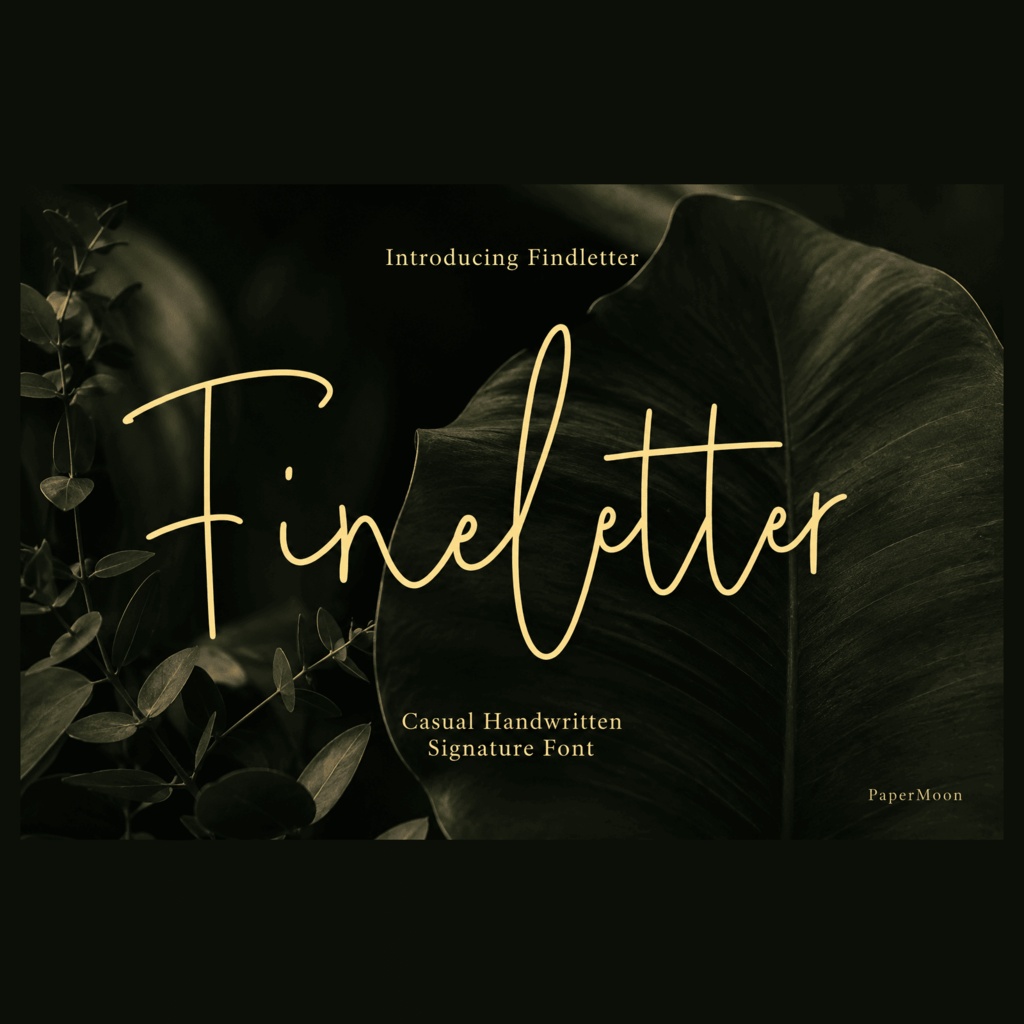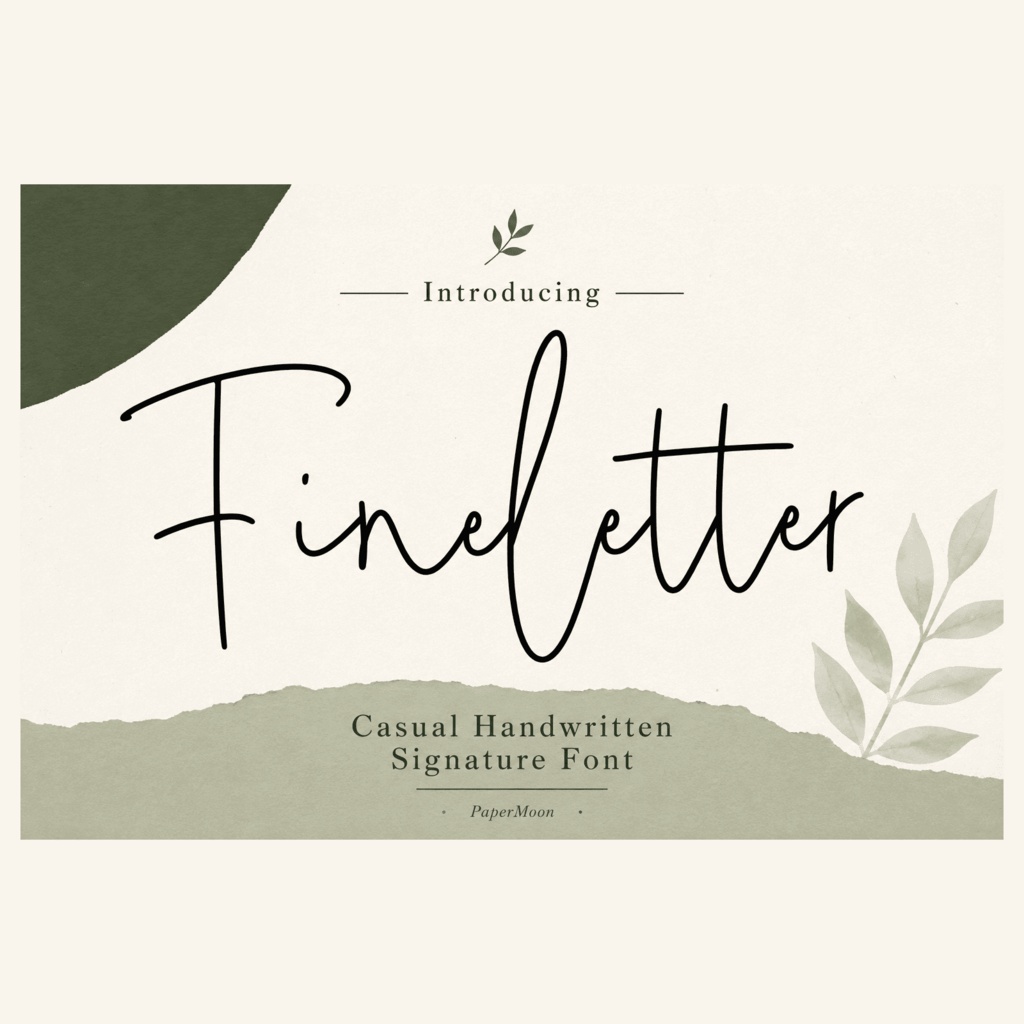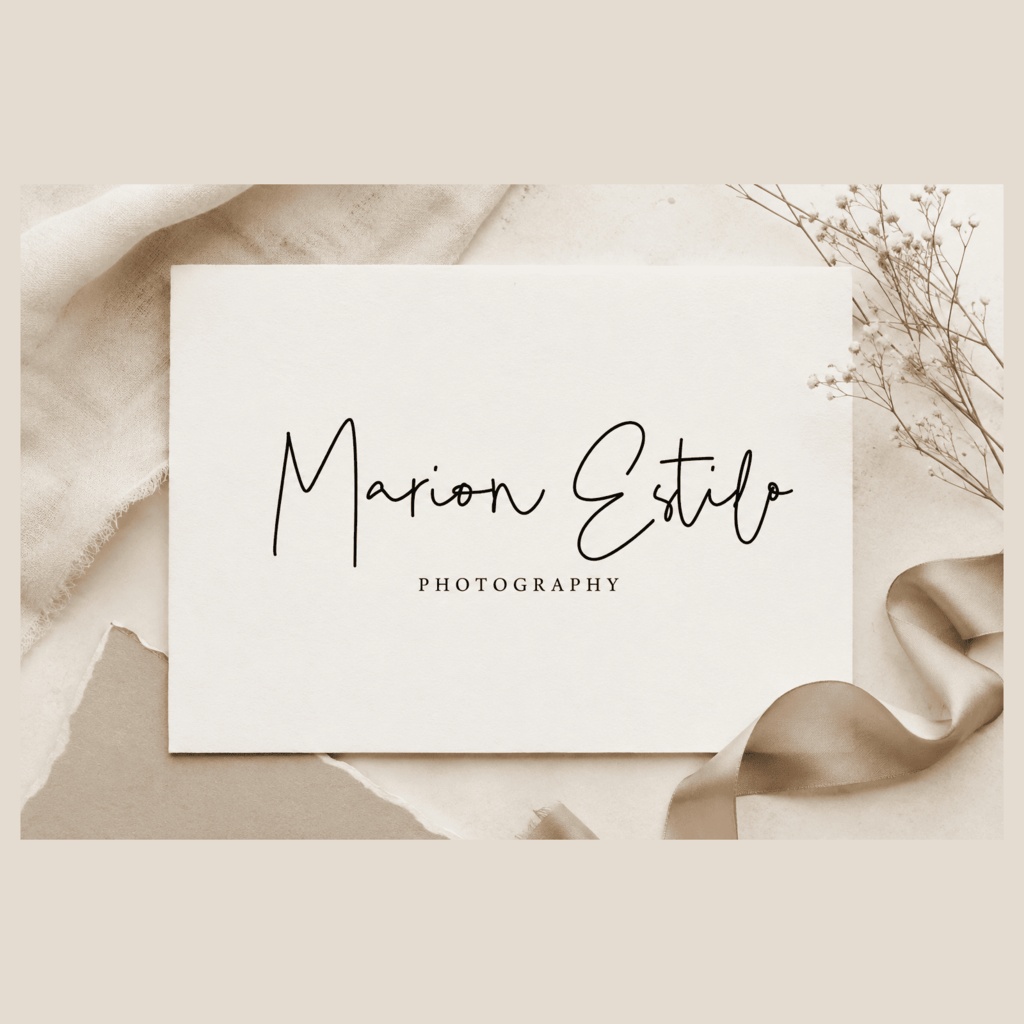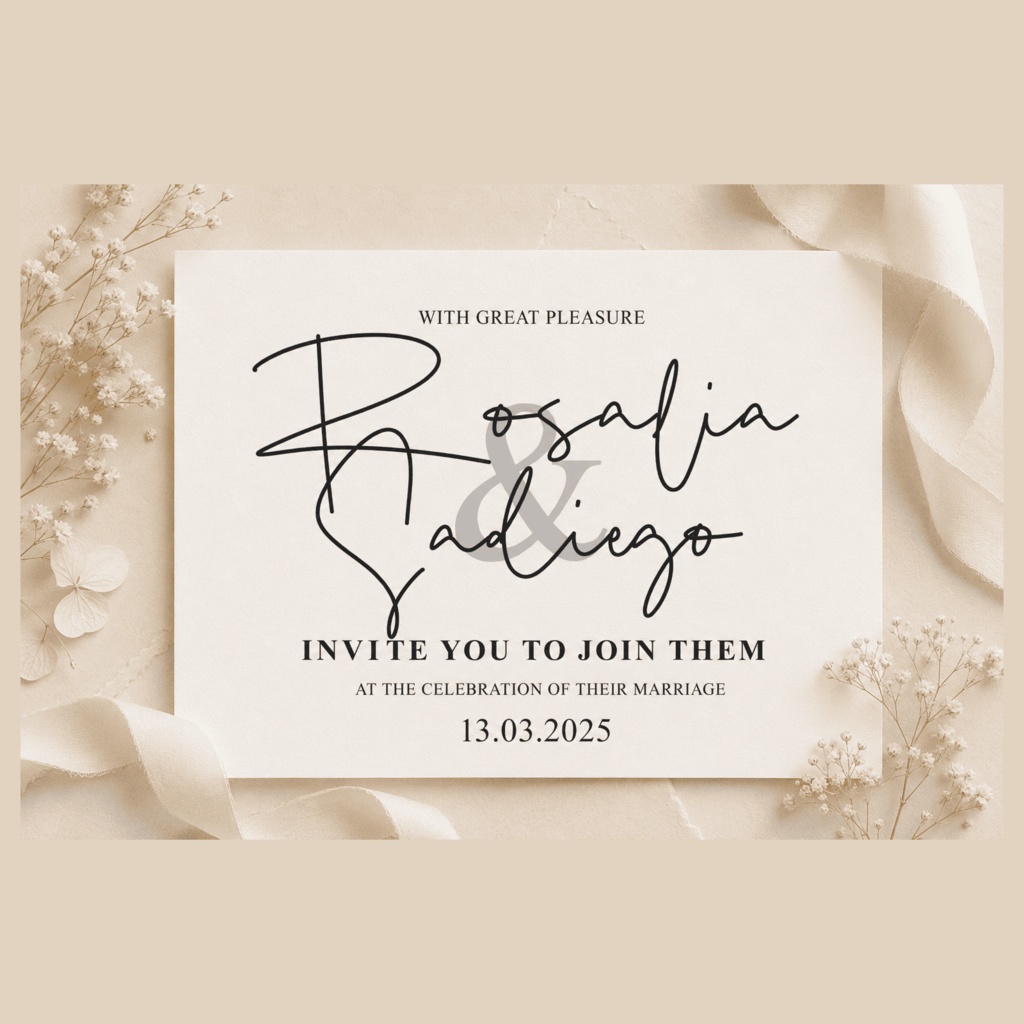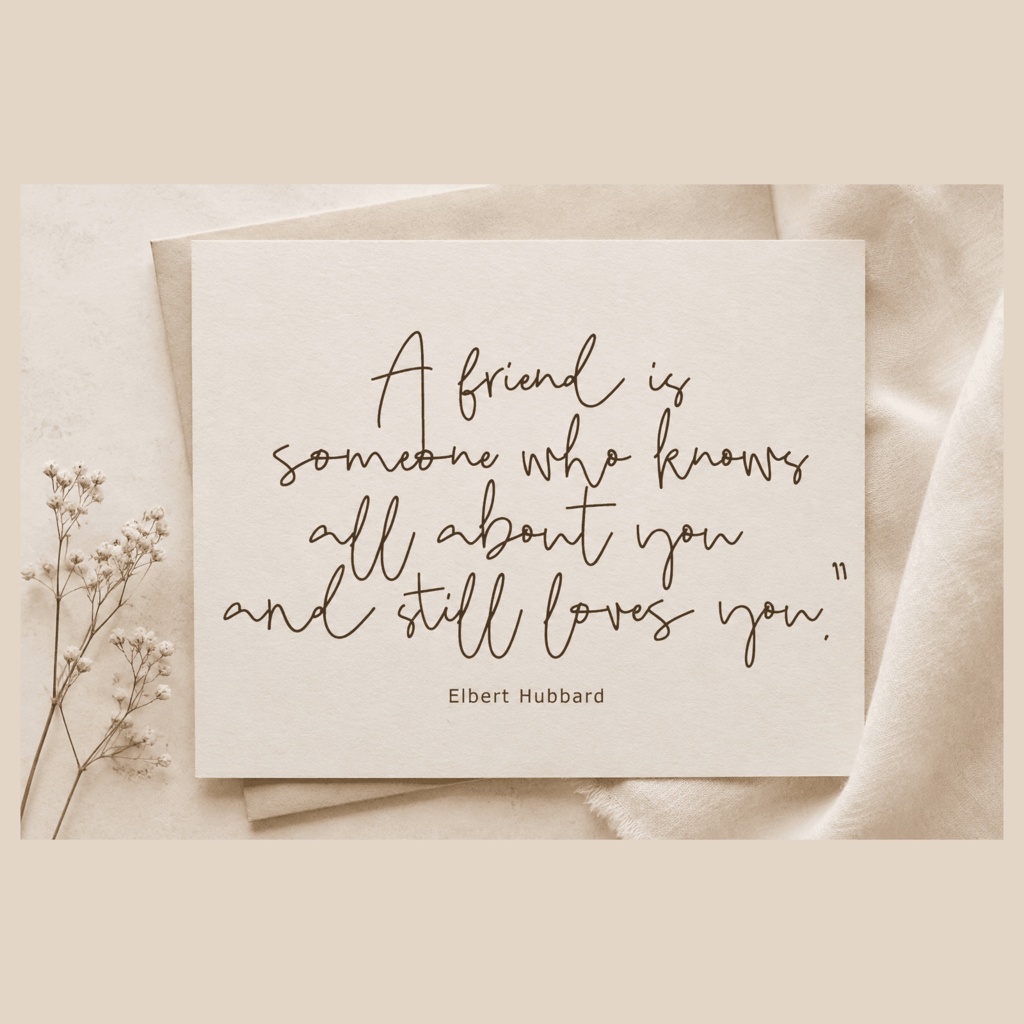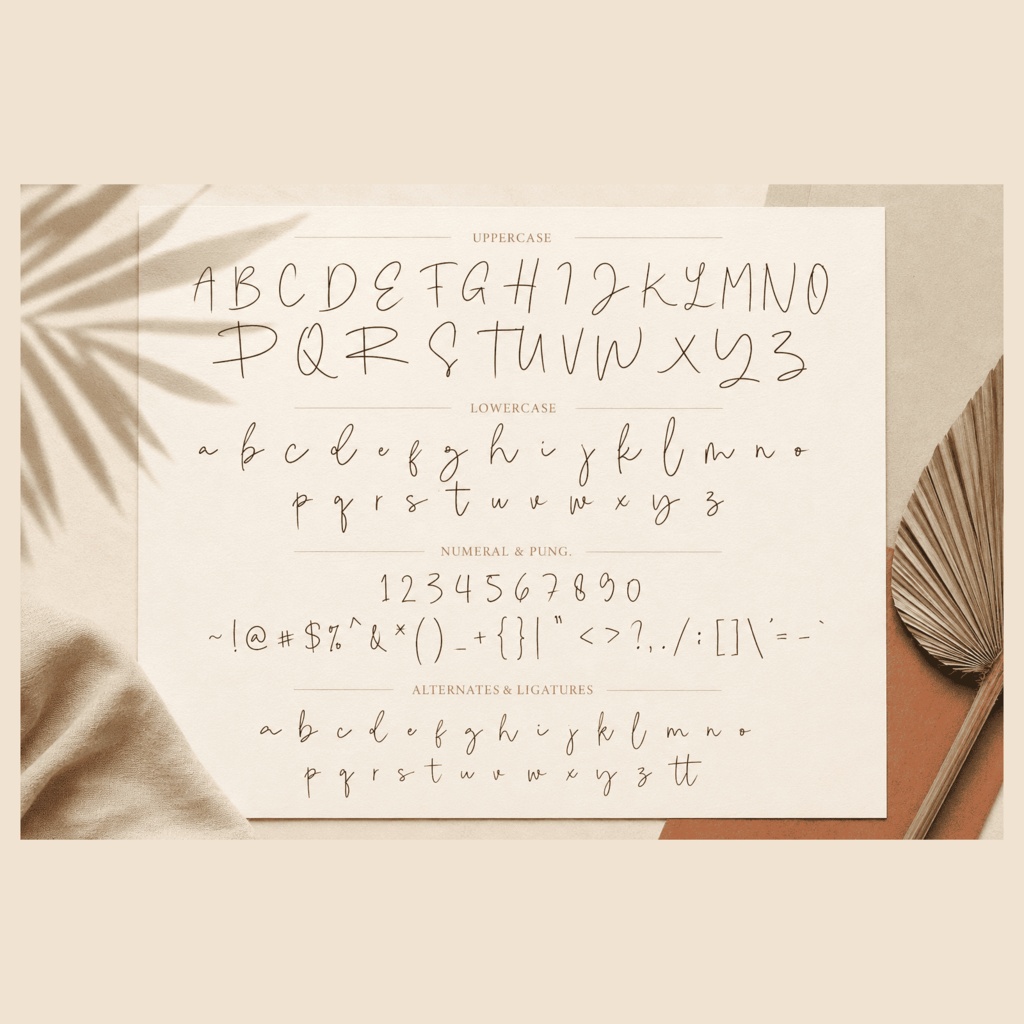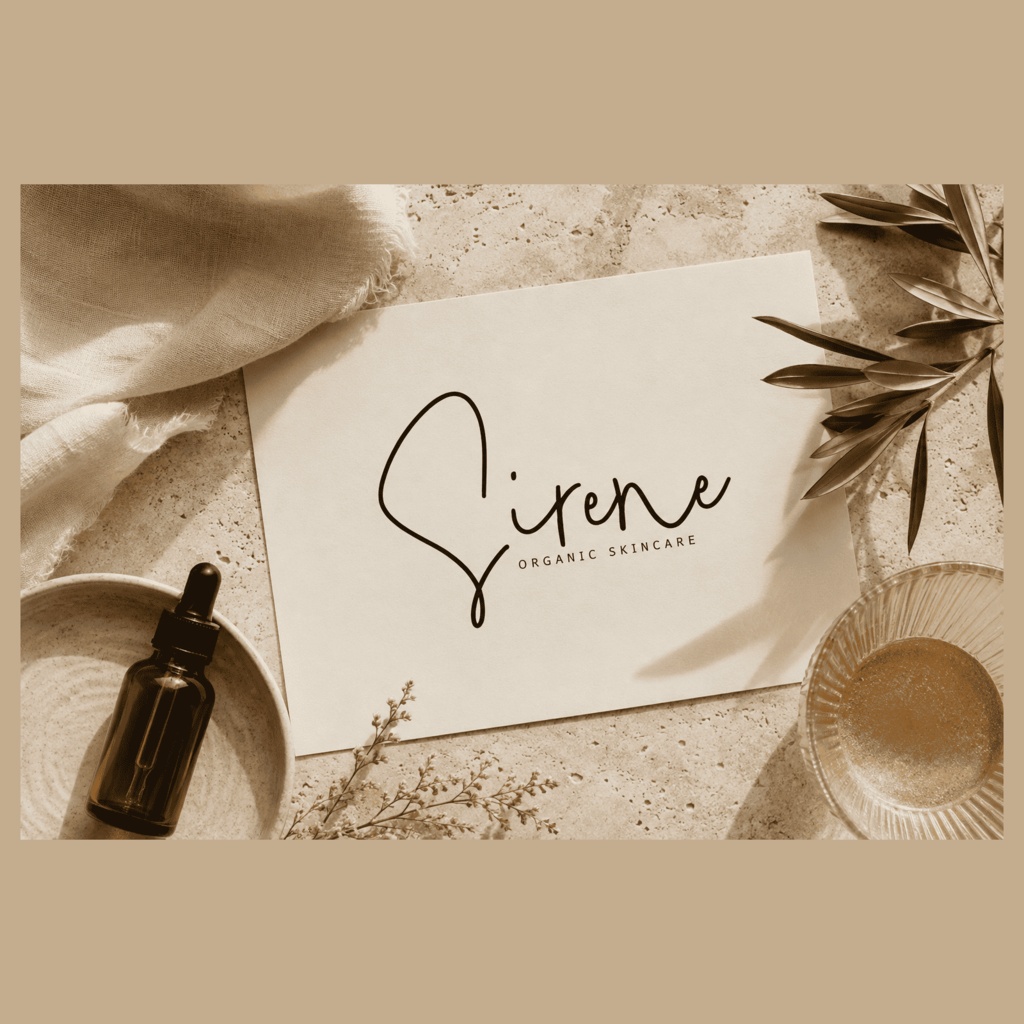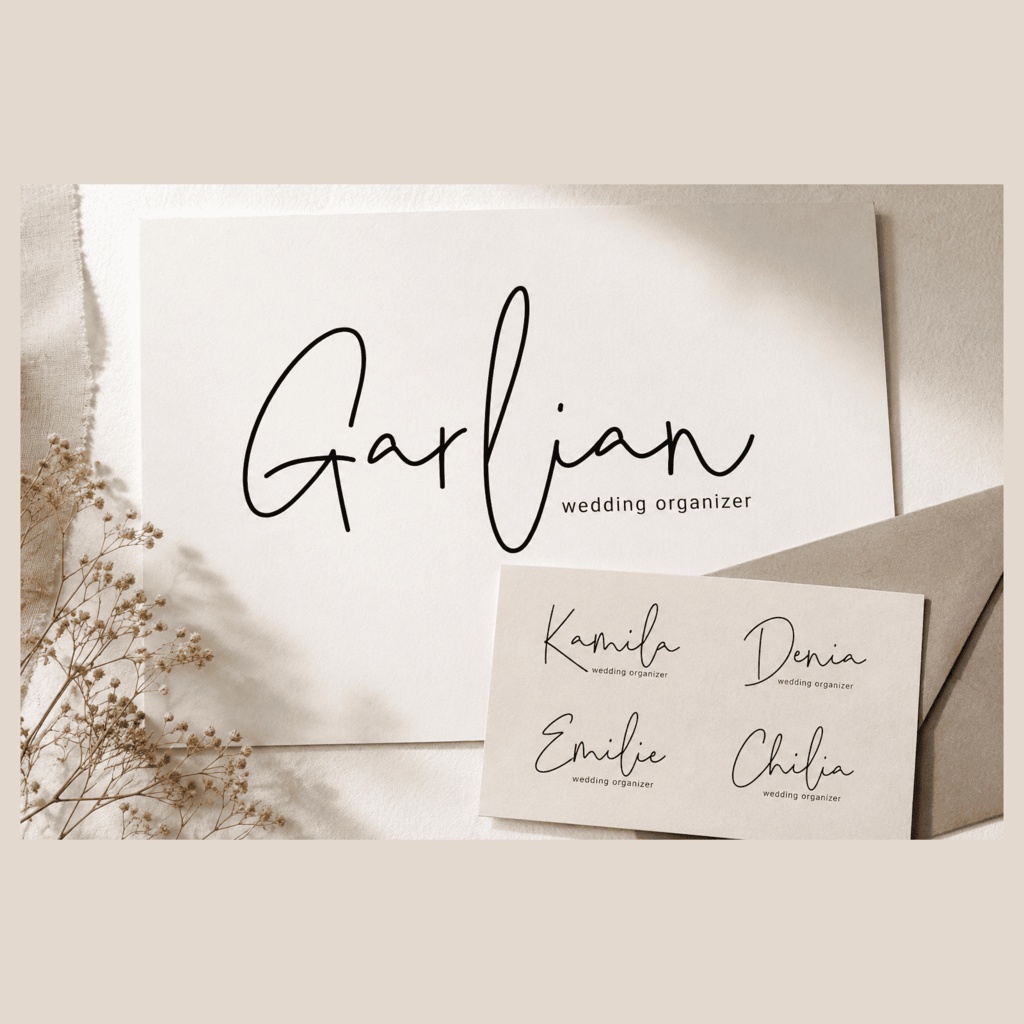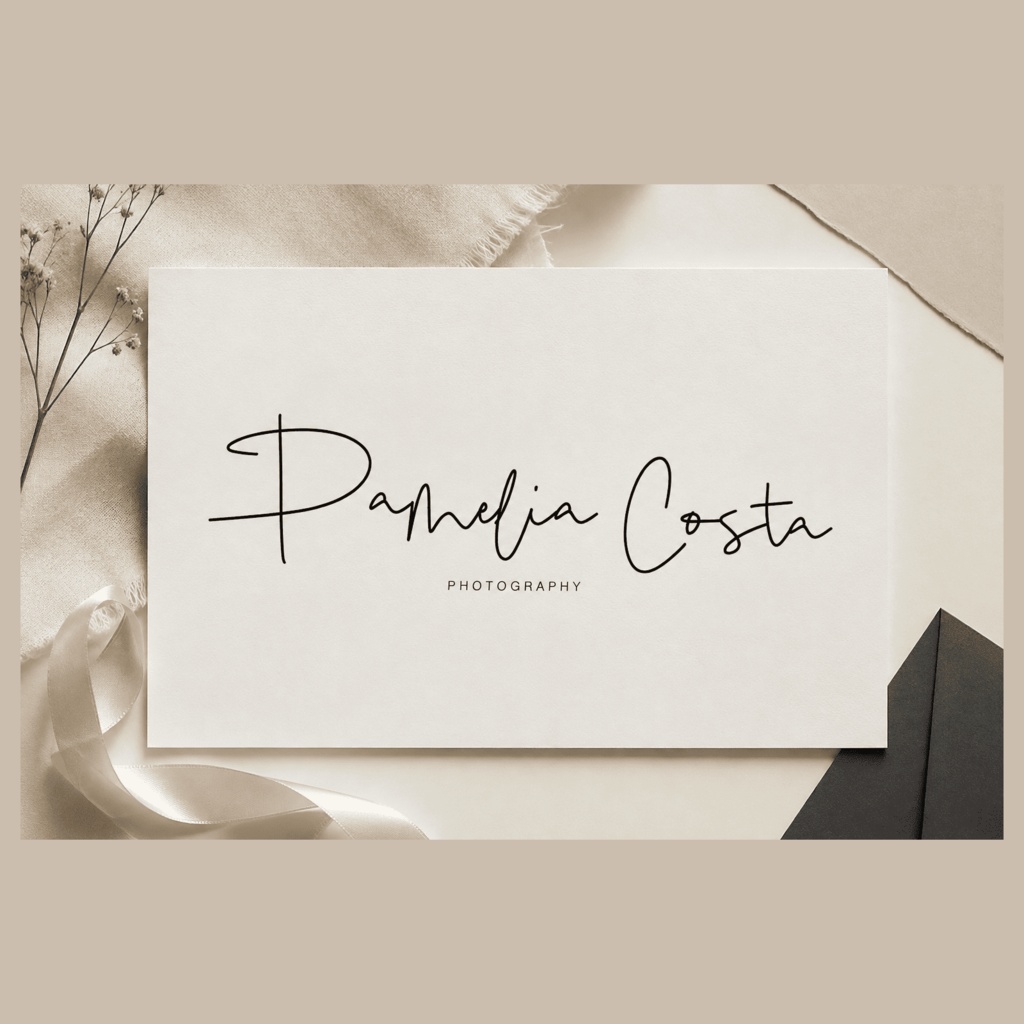
FineLetter | 手書き風の署名系欧文フォント | Handmade Script Font
FineLetterは、手作り感のある署名スタイルと、装飾的な文字、軽やかに揺れるベースラインが特徴の手書き風欧文フォントです。名前や短いフレーズに、個人的で流れるような表情を加えられます。 招待状、グリーティングカード、ブランディング、名刺、引用文、ポスター、署名風ロゴなど、短い見出しやディスプレイ文字におすすめです。文字のリズムを活かしたいデザインや、既製のスクリプト書体よりも温かく個性的な印象を求める作品に向いています。 ### 収録内容 / Included - FineLetter Regular - 214 glyphs - 大文字・小文字、数字、句読点、記号 - GSUB / GPOS layout dataを含むOpenType対応情報 ### 対応文字 / Character Set 大文字・小文字のラテン文字を中心に、数字、句読点、記号を収録しています。日本語・キリル文字・ギリシャ文字を含むか、より広い言語範囲については独立確認されていないため、言語指定のある制作では必要な文字を事前に確認してください。 ### 用途 / Uses ウェディングやイベントの招待状、グリーティングカード、ステーショナリー、ロゴ、ブランディング、名刺、引用文、ポスター、短い見出し、ワードマークなどに。 ### 形式 / Formats OTF / TTF ### 対応環境 / Compatibility OTFまたはTTFに対応するデスクトップ用フォント環境でご利用ください。OpenTypeの動作や装飾文字へのアクセス方法はソフトウェアによって異なるため、使用するアプリケーションのOpenTypeメニューまたはグリフパネルをご確認ください。 ### 利用許諾 / License 利用条件の詳細は、購入時に提示されるライセンス本文をご確認ください。商用利用、埋め込み、再配布、再販などの可否は、確認済みの条件なしには断定していません。 FineLetterで、招待状やロゴ、カード、ポスターに手書きの署名感と自然な動きを加えてください。